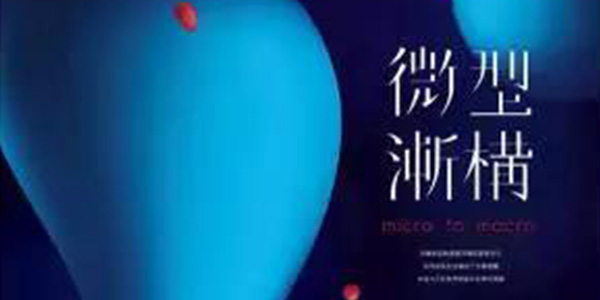
都说流浪地球NB,可除了科幻,它的融入感更值得偷师~
最近流浪地球真是火啊,各种公号都在秀电影色卡、破亿海报啊!
不得不承认,高手确实在民间,但官方海报也并非没有亮眼之处,看这里~
每个人都跟一个字融合在一起,让我想起了黄海设计的《影》。
不过放在一起,感觉有点挤,像叠叠乐一样。
还是“新年快乐”看着舒服,因为“新”和“快”,用的正是汉仪尚巍手书。
由此可见,字体不应该是画面完成后,作为文案最后排版,而是可以成为设计元素,融入整个画面,来看个英文版的~
轨迹法
不过一招鲜也不能吃遍天,还要多看好的创意,比如让文字根据画面,动起来~
你斜我也斜,彼此呼应,实在是妙!
光一个人跳舞,get不到那种韵律,那让英文也舞起来呗~
你凝视深渊的时候,字体也在凝视你。
很难想象,这是1980年瑞士设计师的作品,字母都跟着提线木偶动了。
拆分法
把笔画拆开,在海报中也用得很多,让字体不再那么单一,有了新的视觉。
你可以用想象力替换缺失的部分。
也可以把它作为关键元素。
最重要的是,要跟整个画面如鱼得水~
形态法
如果说前面是在玩文字游戏,到了这一部分,字体真正作为一个C位元素,融在画面里了。
可爱的米奇画风,居然是个韩文。
这个应该能看出来,笔墨间的“山”。
再来个3D阶梯版的,有点晕~
不过也有一看就有画面感的,抓住了精髓。
还有漫画风格的“大人”。
拼图、迷宫一样的布局。
肌理法
肌理看起来最直观,但也是最不容易的,关键就在于材质的表达,比如螺钉+漫画=个性。
用颗粒笔刷表达微尘。
露=水,莹=透,然后就联想到玻璃。
虚和实可能第一想到的就是模糊和清楚,但黑白线条的粗细纵深也能表达~
这个很亲切,看到就想去购物了!
中西融合
最后放一张有感觉的《流浪地球》海报~